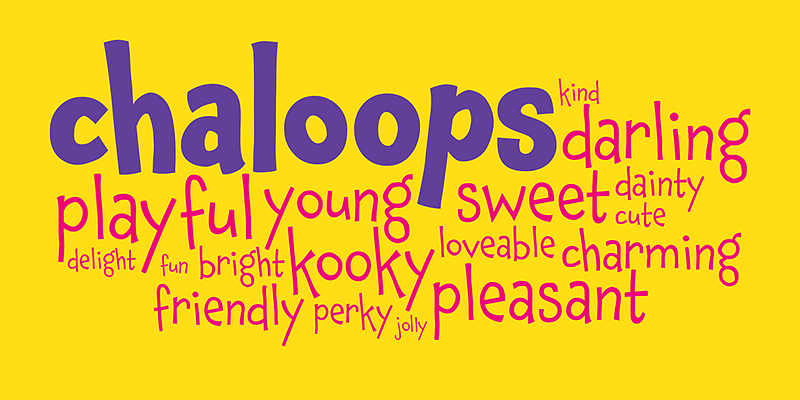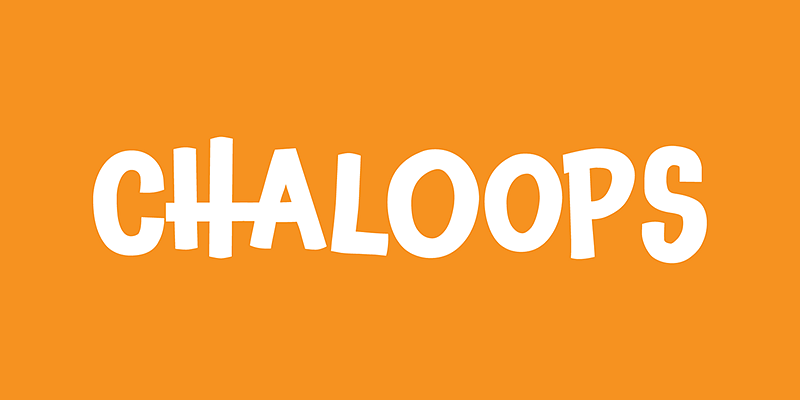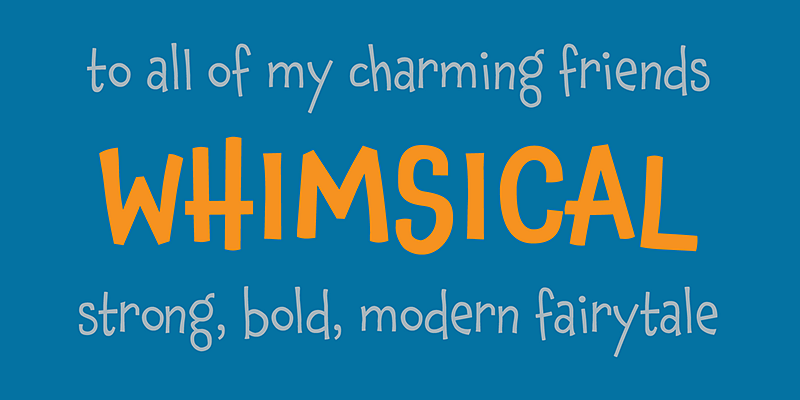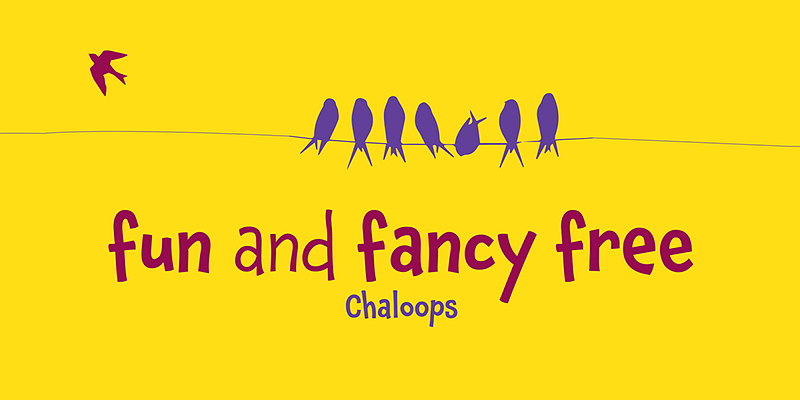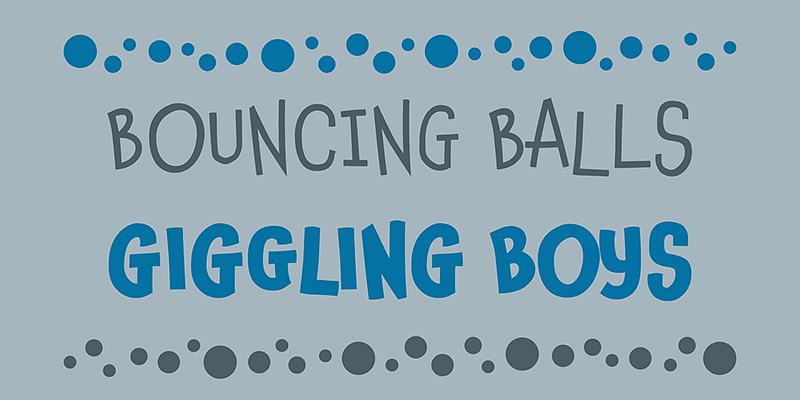
Chank Diesel은 1996년 Chank Co.,를 설립했으며 현재는 미네소타 미니애폴리스에 있는 본사에서 근무하면서 주로 유머, 힘, 개성이 넘치는 디스플레이 서체를 제작하고 있습니다. 그의 글꼴은 부설 스미스소니언 쿠퍼 휴잇 국립 디자인 미술관에 “현대 타이포그래피의 획기적인 사례”로 소개되었습니다.